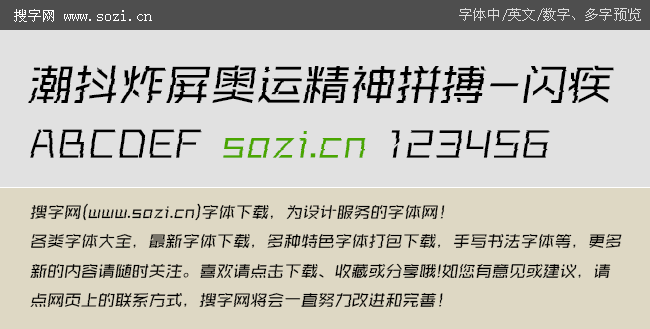
潮抖炸屏奧運精神拼搏-閃疾
搜字網(wǎng)給大家提供一款潮抖炸屏奧運精神拼搏-閃疾中文字體下載,潮抖炸屏奧運精神拼搏-閃疾是一款創(chuàng)意藝術(shù)字體,字體在奧運系列字形基礎(chǔ)上進(jìn)行創(chuàng)新,糅合電音節(jié)奏、潮流風(fēng)尚,賦予字體抖動切割的動態(tài)效果。適合應(yīng)用于藝術(shù)設(shè)計、平面宣傳設(shè)計、網(wǎng)頁設(shè)計、海報設(shè)計等應(yīng)用。